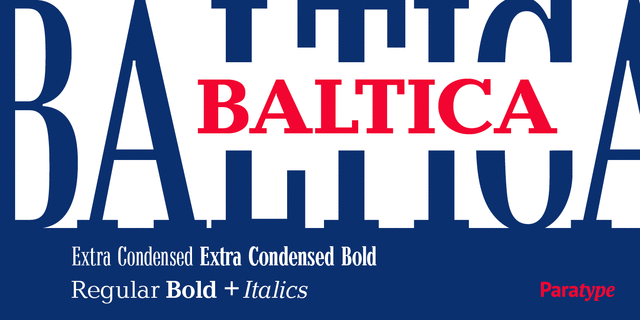
Гарнитура разработана в Отделе наборных шрифтов НПО Полиграфмаш в 1951-52 (коллектив дизайнеров под руководством Веры Чиминовой, при участии Исая Слуцкера) на основе рисунков шрифта Candida фирмы Ludwig & Mayer, 1936 (дизайнер Якоб Эрбар). Форма его знаков близка к брусковым шрифтам, но засечки гораздо более тонкие. Имеет довольно широкие прописные и крупные строчные знаки. Хорошая читаемость в мелких кеглях делает его пригодным для газет и журналов, а ясная форма знаков позволяет использовать в заголовках. Цифровая версия создана в Отделе наборных шрифтов НПО Полиграфмаш в 1988 Александром Тарбеевым. Капитель, дополнительные жирные и сверхузкие начертания разработаны Манвелом Шмавоняном и выпущены фирмой ПараТайп в 2008 году.
Ассоциации c начертанием Baltica Bold
Качества и характер:
мотивирующий ,
ответственный ,
спокойный ,
ровный ,
убедительный ,
понятный ,
деловой ,
уравновешенный ,
техничный ,
прямой ,
точный ,
объективный ,
логичный ,
прагматичный ,
практичный ,
твердый ,
городской ,
строгий ,
серьезный ,
статичный ,
стабильный ,
надежный ,
устойчивый ,
авторитетный ,
уверенный ,
важный ,
качественный ,
резкий ,
острый
Особенности семейства Baltica
Близкий исторический оригинал: